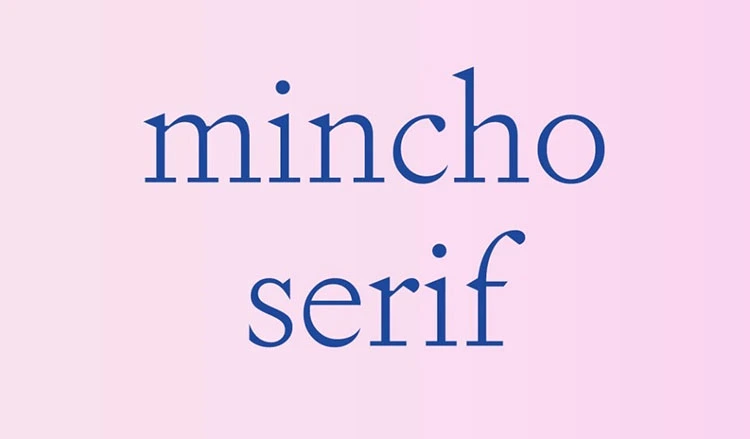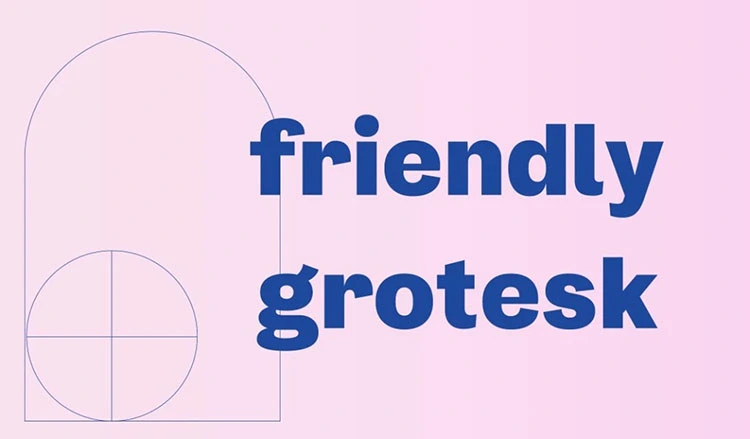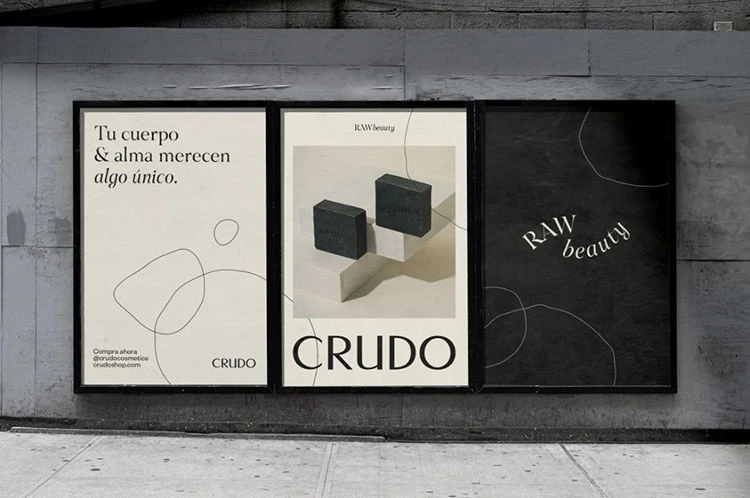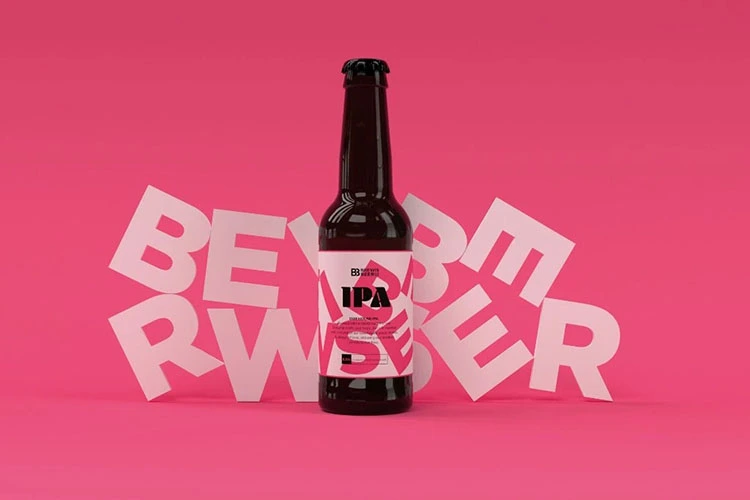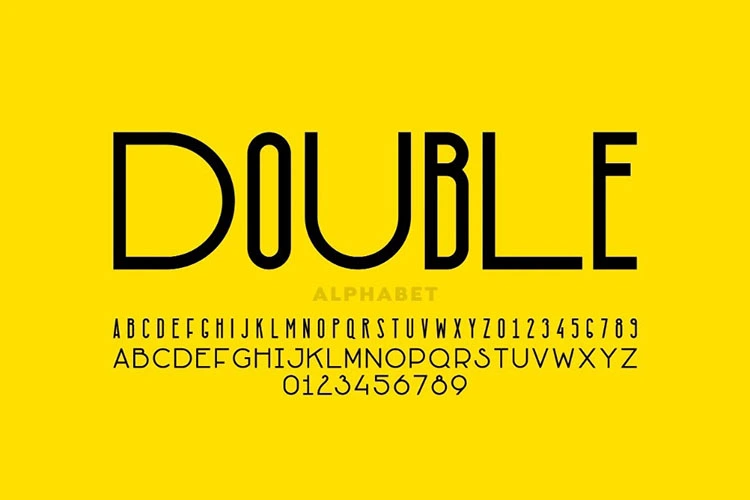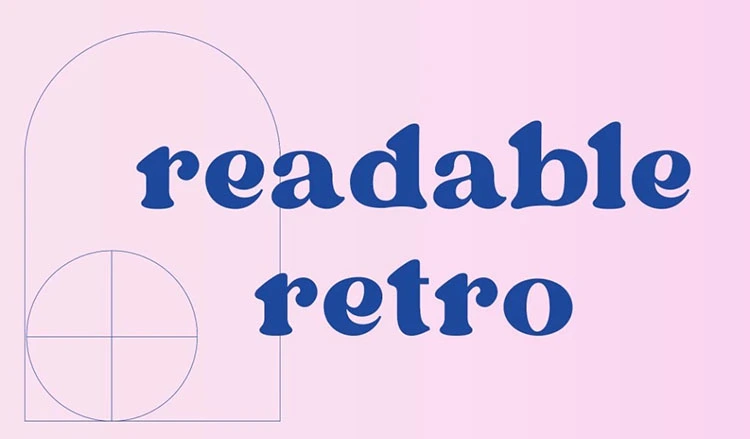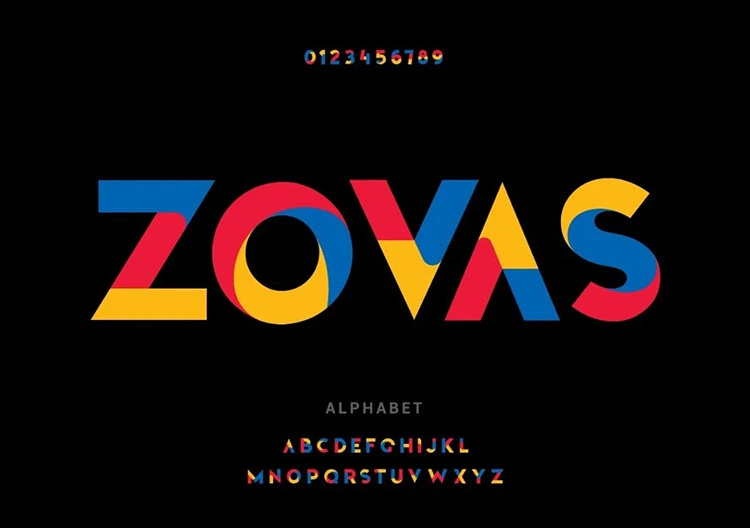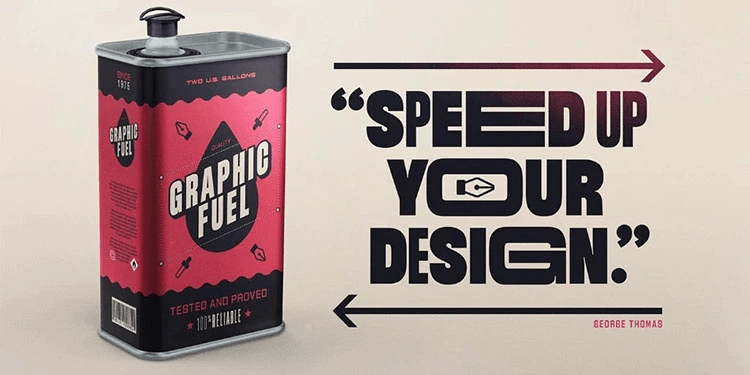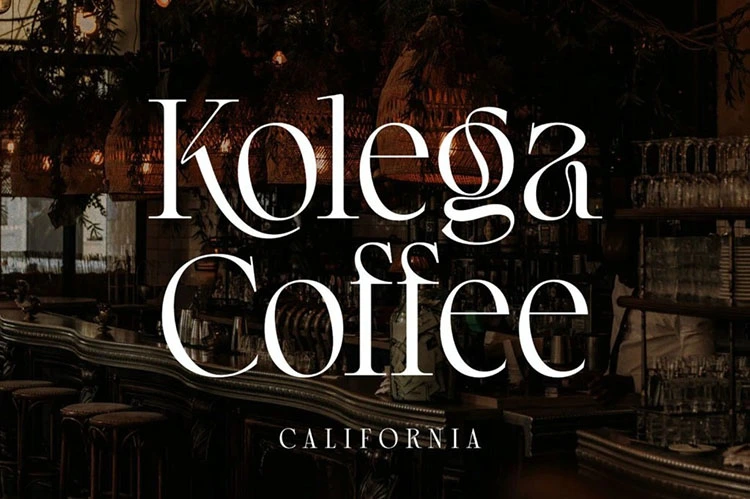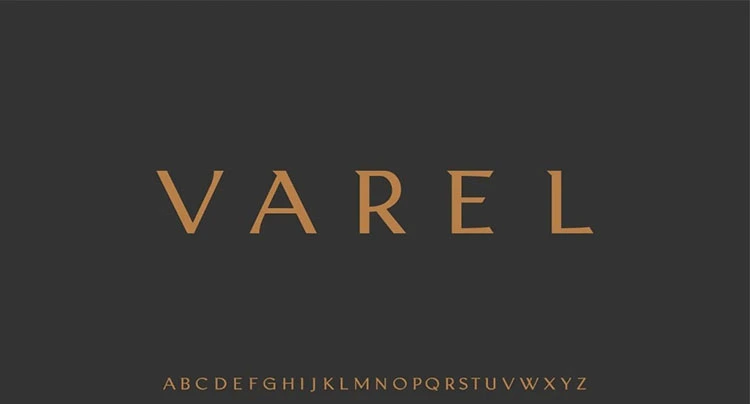
폰트 유형에는 Times New Roman과 Helvetica 이상이 있습니다.
2022년에 디자이너는 많은 선택지로 고민하게 될 겁니다.
트렌드는 변합니다.
이를 명심하면서 2022년에는 어떤 폰트가 유행하게 될까요?
글쎄요, 그런 종류의 예측이 가능한 수정 구슬은 없습니다(있다면 정말 좋았겠죠?).
폰트를 발견하기 위해 셔터스톡은 정보를 위한 데이터, 최근 에이전시 프로젝트, 오늘날 폰트 트렌드를 다듬었습니다.
시대를 반영하는 폰트
폰트 트렌드는 다음과 같습니다.
1. 1930년대 산세리프(1930s sans serif)
2. 혼합된 너비(Mixed width)
3. 유체 디스플레이(Fluid display)
4. 심플 세리프(Simple serif)
5. 상냥한 그로테스크(Friendly grotesk)
6. 민초 세리프(Mincho serif)
7. 읽기 쉬운 레트로(Readable retro)
8. 슈퍼 청키(Super chunky)
1. 1930년대 산세리프(1930s sans serif)
이 온화하게 조각된 산세리프는 아르데코의 개츠비 데카당스를 보여주지는 않지만 대신에, 재즈 시대의 후기 단계에서 힌트를 얻습니다.
이 차분한 산세리프 폰트는 차분한 하이엔드 브랜드 또는 라이프스타일 제품에 아주 잘 어울립니다. 궁극의 절제된 럭셔리를 위해 정교한 세리프 스타일 대신 사용하고 부드러운 흙빛 색상 팔레트와 함께 사용해보세요.
Serena Studio가 디자인한 비누 브랜드 CRUDO의 브랜드 아이덴티티.
디자인 스튜디오 The Nieuw에서 자체 제작한 비주얼 아이덴티티 및 로고타입 디자인.
2. 혼합된 너비(Mixed width)
2022년 폰트 트렌드에서 가장 참신한 것은 혼합된 너비의 타이포그래피가 단순한 그래픽의 매력을 뽐내며 포장, 책 표지 등 다양한 디자인을 위한 대담하고 아름다운 선택이 될 수 있다는 사실입니다.
굵은 산세리프 스타일을 선택하여 폰트의 가독성을 최대화하고 높은 대조의 색상 팔레트를 선택하여 메시지가 돋보이게 하세요.
혼합된 너비의 폰트는 선천적으로 장난스럽기 때문에 조금 더 기발한 작업이 필요한 프로젝트에 사용해보세요.
Double 벡터 폰트 제공 컨트리뷰터 Alhovik.
이미지 제공 Art Grootfontein.
유연성 있고 가변적인 너비의 폰트 제공 Art Grootfontein.
3. 유체 디스플레이(Fluid display)
폰트가 물에 빠진 것처럼 보인다면 제대로 된 스타일인 유체 디스플레이 폰트는 로맨틱하며 천상의 아름다움이 있어 캐주얼한 디자인은 물론 패션이나 라이프스타일 브랜드에도 자연스럽게 어울립니다.
세피아 색조의 사진과 70년대에서 영감을 받은 색 구성표를 결합하여 이 아름다운 폰트의 편안함을 표현해보세요.
Ankita Goswami가 디자인한 Re Skincare를 위한 패키지 디자인.
Regista Grande 모던 디스플레이 폰트.
4. 심플 세리프(Simple serif)
2022년에 세리프 폰트를 트렌디하게 유지하고 싶다면 세리프체 자체(글자 형태 끝에 있는 추가 요소)를 거의 보이지 않게 유지하면서 세리프체와 산세리프체 사이의 중간을 유지해보세요.
이 단순한 세리프 폰트는 매우 다재다능하여 웹 디자인, 매거진 레이아웃 등 다양한 프로젝트에 적용할 수 있습니다.
산세리프 스타일에 세리프를 적용하면 타이포그래피를 힘들이지 않고 우아하게 유지할 수 있습니다.
Ellen Luff이 디자인한 Larken 세리프체.
Varel 럭셔리 벡터 폰트 제공 컨트리뷰터 Zea.lab.
5. 친근한 그로테스크(Friendly grotesk)
그로테스트 서체는 약간의 기발함과 휴머니즘이 담긴 산세리프 폰트입니다. “그로테스크”란 단어는 “작은 동굴로부터”라는 뜻의 독일어에서 유래했으며 19세기에 이러한 폰트 스타일의 일반적인 반응을 나타냅니다.
한때는 원시적이며 어떤 경우에는 완전히 못생겼다고 생각되었던 그로테스크는 오늘날 가장 널리 사용되며 디자이너가 인정하는 폰트입니다.
세리프 폰트가 올해 미니멀리스트 프로젝트의 기준에 부합하지 않는다면 크기가 큰 친근한 그로테스크를 사용해 보세요. 개방적이고 가독성이 뛰어난 이 휴머니스트 산세리프체는 편안한 성격을 가지고 있어 디자인을 보다 쉽게 접근할 수 있고 친근하게 느껴지게 합니다.
그로테스크 스타일을 재기 발랄한 캐릭터, 굵은 두께 또는 낮은 x하이트와 함께 사용해 친근한 요소를 부각해보세요. 이러한 폰트는 특히 어린이 브랜드나 쿨하게 우아하기보다 좀 더 열정적으로 느껴질 필요가 있는 디자인에 잘 어울립니다.
Zovas 벡터 폰트 제공 컨트리뷰터 Beyond Everything.
Attitude 산세리프 벡터 폰트 제공 컨트리뷰터 Zea.lab.
6. 민초 세리프(Mincho serif)
민초 세리프는 고대비의 끈과 캘리그래피 모양의 오래된 일본 폰트 스타일에서 힌트를 얻었습니다. 민초 폰트의 현대적인 곡선은 특히 절제되었으며 동양적인 기원이 명백하지는 않지만 일본 특유의 톤이 느껴지는 차분하고 침착한 분위기를 가지고 있습니다.
민초 세리프는 보기에 아름다울 뿐만 아니라 확실히 가독성이 있어 웹사이트 또는 신호체계에 사용하기 아주 좋습니다. 또한 지적인 특징을 가지고 있어 북 디자인이나 조판 전반에 잘 어울리며 단순한 흑백으로 은은한 우아함을 더합니다.
Bretagne type foundry가 디자인한 Self Modern 민초 타이포그래피.
Google Font에서 다운로드 가능한 FONTDASU 디자인의 Shippori Mincho.
7. 읽기 쉬운 레트로(Readable retro)
온라인 접근성 문제에 대한 인식이 높아지면서 타이포그래피 세계에 긍정적인 영향을 미쳤습니다. 한때는 거의 읽을 수 없었던 참신한 폰트들이 필요하다고 여겨졌지만 이 가독성이 떨어지는 폰트들은 시각 장애가 있는 사용자가 더 쉽게 사용할 수 있어야 하는 사이트에서 잘리지 않았습니다.
이러한 펑키한 폰트 스타일 중 일부를 단순화하고 더 읽기 쉽게 구현해 보세요. 읽기 쉬운 레트로 글꼴은 이러한 복고풍 스타일의 본질을 유지하면서도 불필요한 과잉을 제거합니다. 더 날렵하고 두툼한 이 제품은 빈티지와 현대성을 결합하여 향수를 불러일으킵니다.
가독성이 뛰어난 복고 활자 실행의 가장 주목할만한 예 중 하나는 &Walsh의 수직 농장 기업 Plenty의 최신 브랜드 아이덴티티입니다.
레트로에서 영감을 받은 폰트는 상당한 재미가 있어 제품이 접근 가능하면서 아주 기분 좋게 느껴지게 만듭니다. 이 아이덴티티가 앞으로 몇 달 안에 더 읽기 쉬운 복고풍 서체를 촉발하는 것을 기대하세요.
Dubbo 레트로 폰트.
샐러드 리테일러 Plenty by &Walsh를 위한 브랜드 아이덴티티.
8. 슈퍼 청키(Super chunky)
2022년에도 브랜드는 경쟁의 바다에서 돋보일 수 있는 더 많은 방법을 계속 모색할 것입니다. 대담하고 아주 굵은 타이포그래피는 눈을 사로잡으며 기억할만하고 큰 크기로 설정했을 때 특히 효과적입니다.
포장 디자인에 그래픽이나 일러스트레이션 대신 사용하고 강렬한 고대비 색상을 함께 사용하여 효과를 극대화해보세요.
추가적인 스타일 포인트로 이 굵은 폰트를 배경이나 아이콘의 개별 그래픽으로 사용해보세요. 활자 스타일의 캐릭터를 뒤섞어 폰트 기반 디자인에 더 많은 재미와 개성을 부여해보세요.
Tom Sutton and Luke Dryden가 디자인한 Brewis Beer의 패키지 디자인.
Mega Bold 벡터 폰트 제공 컨트리뷰터 Mott Jordan.
두꺼운 Fight 벡터 폰트 제공 컨트리뷰터 fontStocker.